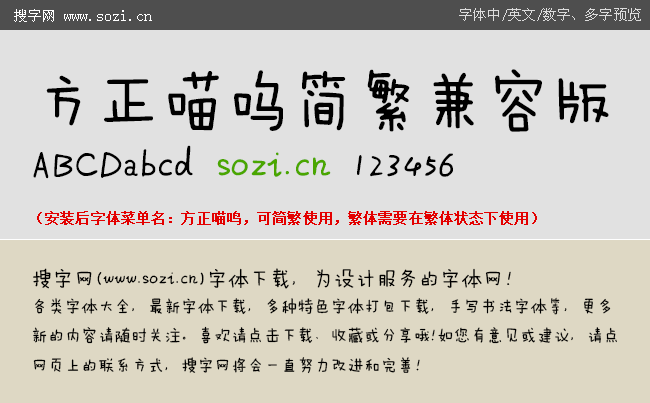
方正喵嗚簡(jiǎn)繁兼容版(FZMM)
搜字網(wǎng)給大家提供一款非?蓯鄣姆秸鲉梵w卡通字體下載,方正喵嗚體是少女漫畫家喵嗚聯(lián)手方正出品的一款手寫涂鴉字體,字形活潑、可愛、隨意,給人一種無憂無慮毫無約束的自由之感,適合兒童產(chǎn)品、海報(bào)排版、包裝設(shè)計(jì)等廣告宣傳使用。